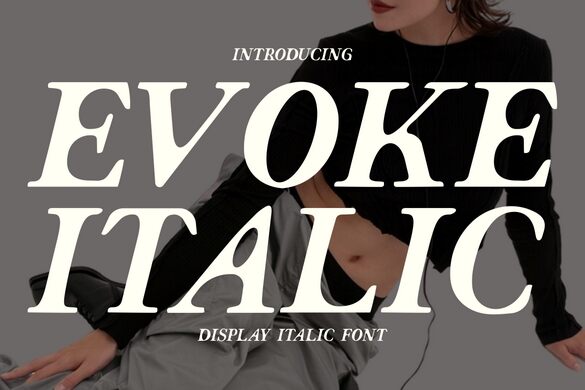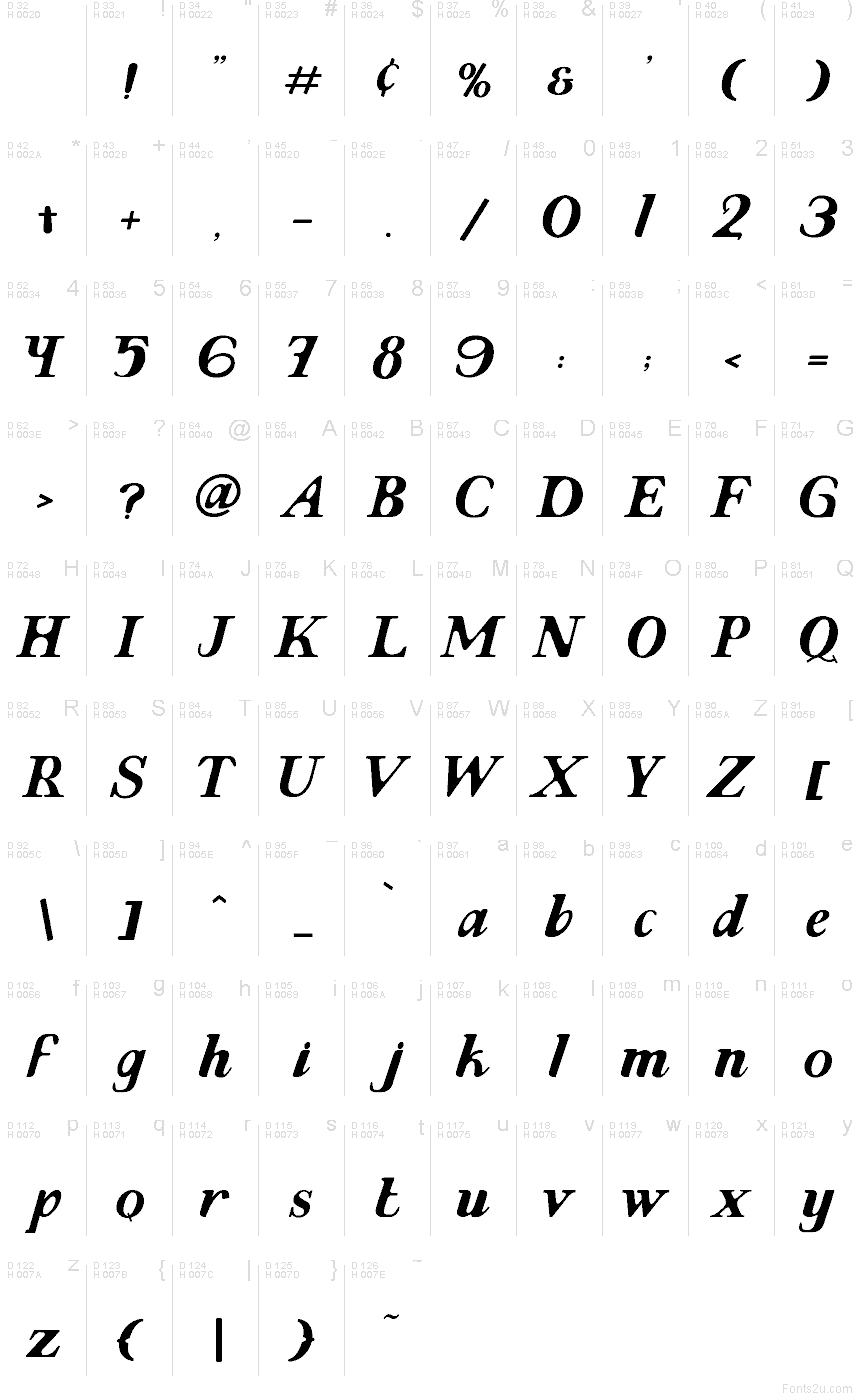
Evoke Italic von Shanaf Studio ist eine kostenlose kursive Display-Schrift, die von einem fließenden, kalligraphischen Rhythmus und weichen, traditionellen Serifenelementen geprägt ist. Die Buchstaben neigen sich nach vorne, geprägt von langen, schwungvollen Kurven und spitz zulaufenden Verbindungen. Dies verleiht dem Design einen theatralischen Rhythmus, der eher an redaktionelle Handschrift erinnert als an eine neutrale kursive Schrift.
Diese Dynamik verleiht kurzen Überschriften, Buchtiteln, Magazinköpfen, Verpackungsdesigns und Branding für Cafés eine klare, fokussierte Wirkung, ohne dass zusätzliche Ornamente erforderlich sind. Sie eignet sich zudem hervorragend für Zitatgrafiken sowie für Mode- oder Beauty-Promotions, wo die geschwungenen Striche und eleganten, swash-artigen Endungen einzelne Wörter selbstbewusst in Szene setzen.